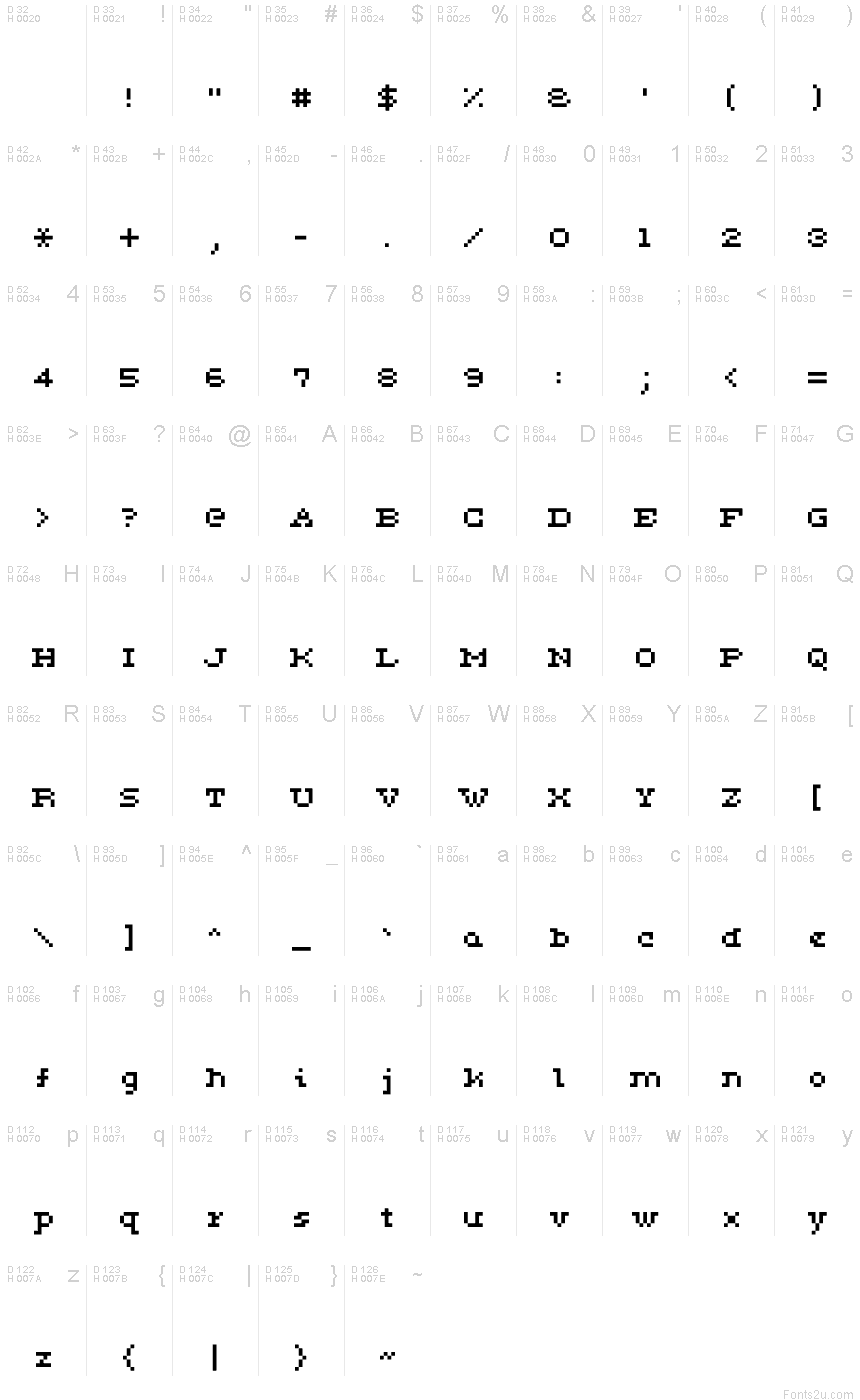
Ceriph 05_53 autorstwa Craiga Kroegera to darmowy szeryfowy font bitmapowy w klimacie surowych, wczesnych ekranów komputerowych. Znaki są zbudowane z grubych, kwadratowych pikseli, ale obecność szeryfów sprawia, że nie wydaje się on jedynie czysto użytkowy – ma w sobie coś z wyrazistego, niemal literackiego rytmu, który przywodzi na myśl dawne interfejsy i publikacje o niskiej rozdzielczości.
Naturalnie pasuje do menu gier retro, nagłówków w zinach, odznak internetowych, tagów na plakatach i kompaktowych tytułów, gdzie pikselowa siatka jest częścią przekazu. Jako darmowy font świetnie sprawdzi się też w krótkich tekstach czy eksperymentach z logotypem, które potrzebują blokowej, cyfrowej tekstury z odpowiednią domieszką szeryfowego charakteru, aby wyglądać ciekawiej niż zwykły systemowy bitmap.